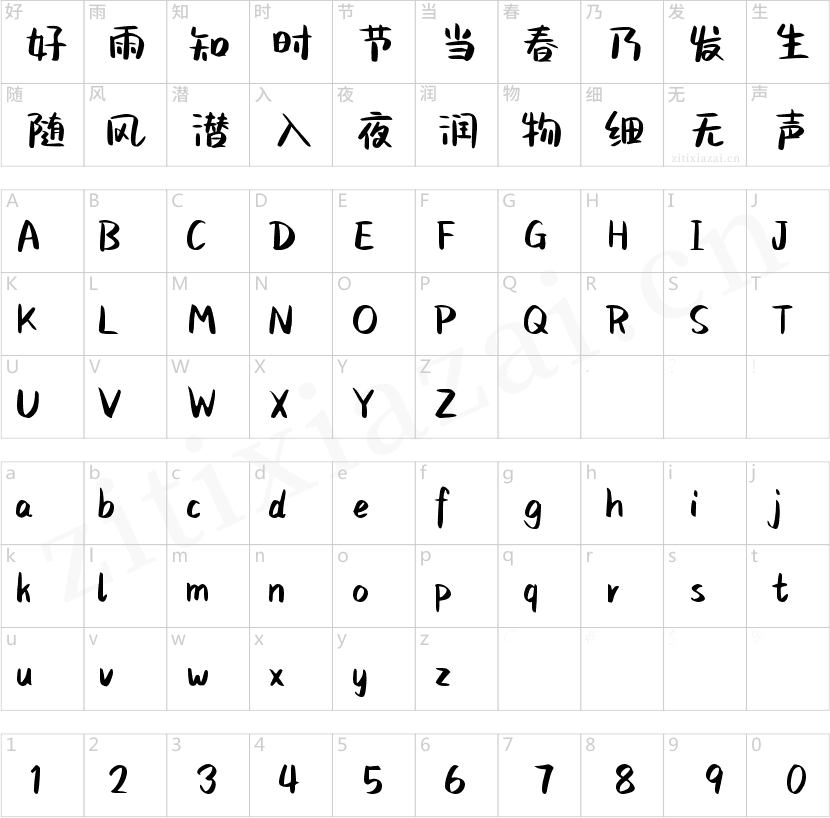
Aa猫哆哩
Aa猫哆哩字体
Aa猫哆哩是一款非常具有艺术性的字体,它的设计灵感来源于对古典艺术的研究,同时又融入了现代字体设计的元素。字形优美,笔画粗细变化自然,给人以大气、典雅的感觉。Aa猫哆哩是一款既传统又现代的字体,它的设计充满艺术感,美观大方,实用性也非常强。无论是对于设计师还是对于普通读者来说,都是一种非常不错的字体选择。Aa猫哆哩适合用于具有艺术感的场合,比如海报、宣传单张、书籍封面等。由于其字形流畅且具有动态感,也适合用于大量的文本排版,如报纸、杂志等。